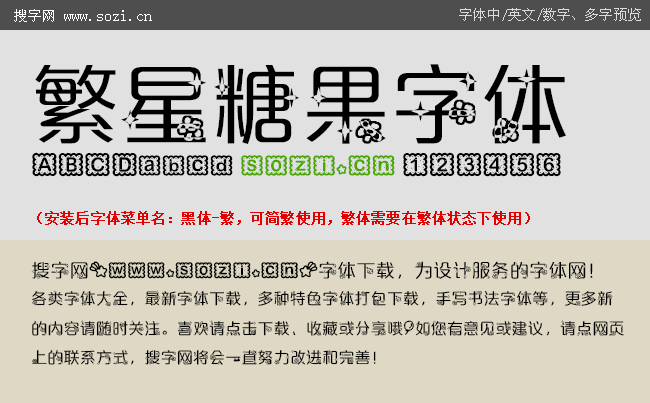
繁星糖果字體
搜字網(wǎng)給大家提供一款名為繁星糖果字體手機(jī)中文字體下載。這款手機(jī)字體是在字體筆畫間點(diǎn)綴了有趣的星星與糖果卡通圖案,在保持文字的識(shí)別性的同時(shí),又點(diǎn)綴一點(diǎn)趣味卡通圖案,趣味性實(shí)足,喜歡的朋友安裝一下吧。